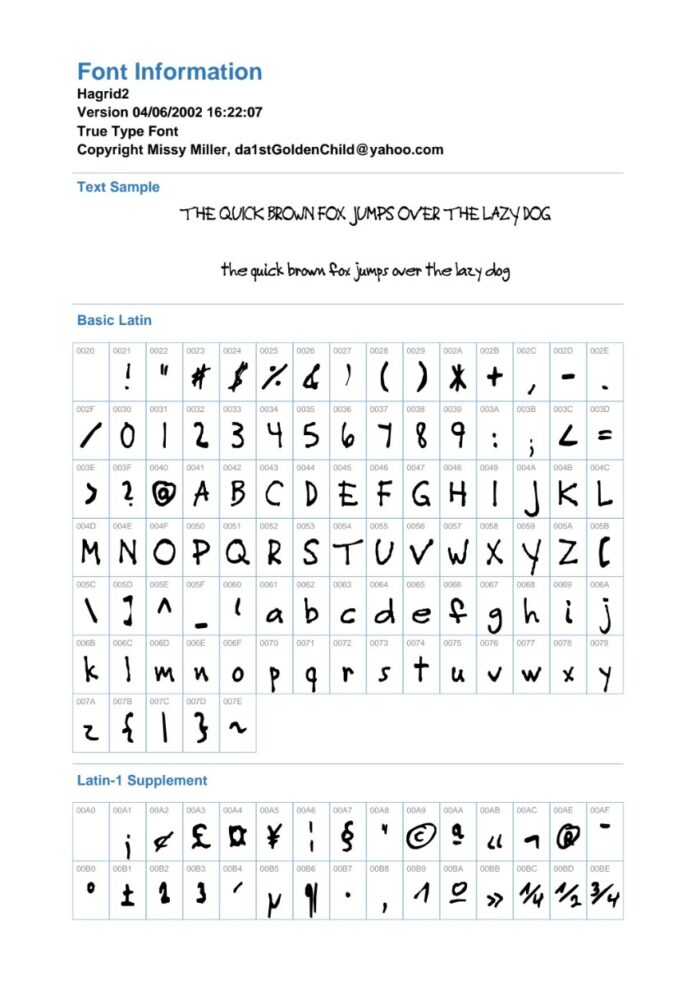
Font Chữ Hagrid Độc Đáo
Font Chữ Hagrid Độc Đáo. Khám phá font chữ Hagrid độc đáo, mang phong cách viết tay tự nhiên và cá tính. Hoàn hảo cho các thiết kế cần sự sáng tạo, gần gũi và không kém phần chuyên nghiệp. Tải ngay tại Poster.vn để tạo điểm nhấn cho dự án của bạn.
Trong thế giới thiết kế đồ họa, việc lựa chọn một font chữ phù hợp có thể tạo nên sự khác biệt lớn cho tác phẩm của bạn. Font chữ Hagrid là một lựa chọn tuyệt vời cho những ai đang tìm kiếm sự độc đáo, cá tính và một chút gì đó hoài cổ. Với phong cách viết tay tự nhiên, Hagrid mang đến cảm giác gần gũi, chân thực và đầy tính nghệ thuật. Tại Poster.vn, chúng tôi tự hào mang đến cho bạn tài nguyên font chữ Hagrid chất lượng cao, giúp bạn dễ dàng nâng tầm các dự án thiết kế của mình.
Font Chữ Hagrid Là Gì?
Font chữ Hagrid là một kiểu chữ viết tay (handwritten font) được thiết kế với những nét vẽ tự do, phóng khoáng, mô phỏng chữ viết của một người. Đặc điểm nổi bật của font này là sự không hoàn hảo có chủ đích, tạo nên vẻ đẹp riêng biệt và không trùng lặp. Mỗi ký tự đều có một chút biến thể, mang lại cảm giác chân thực như được viết bằng tay. Điều này làm cho Hagrid trở thành lựa chọn lý tưởng cho các thiết kế cần sự ấm áp, cá nhân hóa và một chút nét cổ điển.
Đặc Điểm Nổi Bật Của Font Chữ Hagrid
• Phong cách viết tay tự nhiên: Các nét chữ mô phỏng hoàn hảo chữ viết tay, mang lại cảm giác gần gũi và thân thiện.
• Tính cá nhân hóa cao: Thích hợp cho các dự án muốn thể hiện sự độc đáo và không theo khuôn mẫu.
• Dễ đọc: Mặc dù là font viết tay, Hagrid vẫn đảm bảo tính dễ đọc, phù hợp cho nhiều mục đích sử dụng.
• Đa dạng ký tự: Hỗ trợ đầy đủ các ký tự Latin cơ bản, số và một số ký tự đặc biệt, giúp bạn thoải mái sáng tạo.
Ứng Dụng Của Font Chữ Hagrid Trong Thiết Kế
Với vẻ ngoài độc đáo của mình, font chữ Hagrid có thể được ứng dụng trong rất nhiều lĩnh vực thiết kế khác nhau. Sự linh hoạt của nó cho phép bạn tạo ra những sản phẩm ấn tượng và thu hút.
Thiết Kế Thương Hiệu và Logo
Nếu bạn muốn thương hiệu của mình nổi bật với một phong cách riêng, Hagrid là một lựa chọn tuyệt vời. Nó có thể được sử dụng để thiết kế logo cho các cửa hàng thủ công, quán cà phê, tiệm bánh, hoặc các thương hiệu mang tính cá nhân cao. Sự ấm áp và chân thực của font chữ sẽ giúp khách hàng cảm thấy gần gũi hơn với thương hiệu của bạn.
Thiết Kế Ấn Phẩm Quảng Cáo
Font chữ Hagrid rất phù hợp cho các ấn phẩm quảng cáo như poster, flyer, banner, đặc biệt là những ấn phẩm dành cho các sự kiện văn hóa, nghệ thuật, hoặc các chương trình khuyến mãi mang tính chất thân mật. Nó giúp thông điệp của bạn trở nên nổi bật và dễ nhớ hơn.
Thiết Kế Sách, Tạp Chí và Blog
Để tạo điểm nhấn cho tiêu đề, trích dẫn hoặc các phần đặc biệt trong sách, tạp chí hoặc blog, Hagrid sẽ mang lại một cái nhìn mới mẻ và thu hút. Nó phá vỡ sự đơn điệu của các font chữ truyền thống, tạo ra sự hứng thú cho người đọc.
Thiết Kế Thiệp Mời và Thẻ Chúc Mừng
Với phong cách viết tay, Hagrid là lựa chọn hoàn hảo cho các thiệp mời sinh nhật, thiệp cưới, thiệp chúc mừng hoặc các loại thẻ quà tặng. Nó tạo ra cảm giác cá nhân hóa, như thể bạn đã tự tay viết những lời chúc đó.
Cách Sử Dụng Font Chữ Hagrid Hiệu Quả
Để tận dụng tối đa vẻ đẹp của font chữ Hagrid, bạn cần lưu ý một số điểm sau:
• Kết hợp hài hòa: Hagrid thường đẹp nhất khi được kết hợp với các font chữ sans-serif hoặc serif đơn giản, sạch sẽ để tạo sự cân bằng.
• Kích thước phù hợp: Do tính chất viết tay, Hagrid có thể khó đọc ở kích thước quá nhỏ. Hãy đảm bảo sử dụng nó ở kích thước đủ lớn để dễ dàng nhận diện.
• Màu sắc: Thử nghiệm với các gam màu khác nhau để xem màu nào làm nổi bật Hagrid nhất trong thiết kế của bạn. Các màu sắc ấm áp, tự nhiên thường rất hợp với font này.
• Không lạm dụng: Mặc dù đẹp, nhưng việc sử dụng quá nhiều font chữ viết tay trong một thiết kế có thể gây rối mắt. Hãy dùng Hagrid làm điểm nhấn thay vì font chữ chính cho toàn bộ văn bản dài.